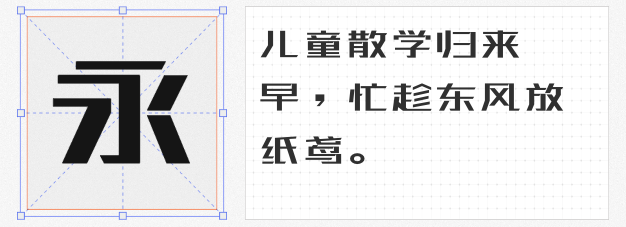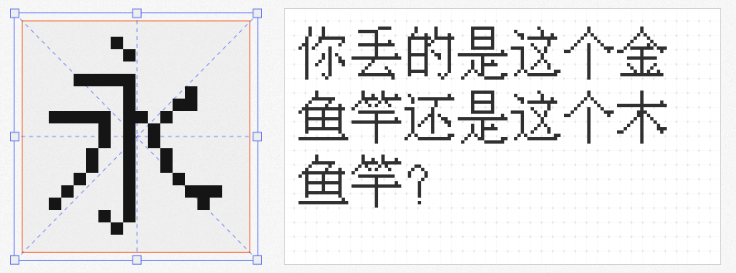
作为一款无衬线字体,金山云技术体以年轻、硬朗的视觉风格脱颖而出。其笔画粗细均匀,转折处采用直角处理,搭配略微收窄的字腔结构,既保留了黑体的简洁感,又通过细节锐化传递出科技行业的进取精神。无论是科技产品海报、互联网品牌视觉,还是运动类设计的标题用字,这款字体都能以干净利落的形态强化现代感,尤其适合需要突出“专业”“高效”的场景。
站酷高端黑以简洁明朗的笔画与果断有力的笔势,构建出极具冲击力的视觉语言。其字形设计摒弃冗余装饰,通过粗细对比与节奏感强化力量感,同时保持了良好的识别性。无论是促销活动的醒目标语、广告海报的核心文案,还是品牌标语的视觉呈现,这款字体都能以锐气十足的姿态吸引目光,尤其适合需要传递“年轻”“进取”态度的商业场景。
基于优设标题黑的经典框架,标题圆将犀利的尖角转化为圆润弧线,在保留力量感的同时注入柔和气质。这种“外柔内刚”的设计哲学,使其既能胜任科技、运动类标题的视觉冲击,又能通过圆角细节传递人文关怀,适合教育、公益、生活方式类品牌的视觉表达。其高辨识度与屏显适配性,更让它成为社交媒体、移动端设计的理想选择。
作为ChuLyu字体的升级版,粗柳坊新16x以手写质感为基底,通过粗细均匀的笔画与略带拙趣的形态,营造出复古与新潮交织的独特氛围。其字形结构松散却不失平衡,适合需要传递“个性”“原创”态度的设计场景,如文创产品包装、独立品牌视觉、音乐节海报等。这款字体的自由感,能为商业项目注入人文温度,打破工业化设计的冰冷感。